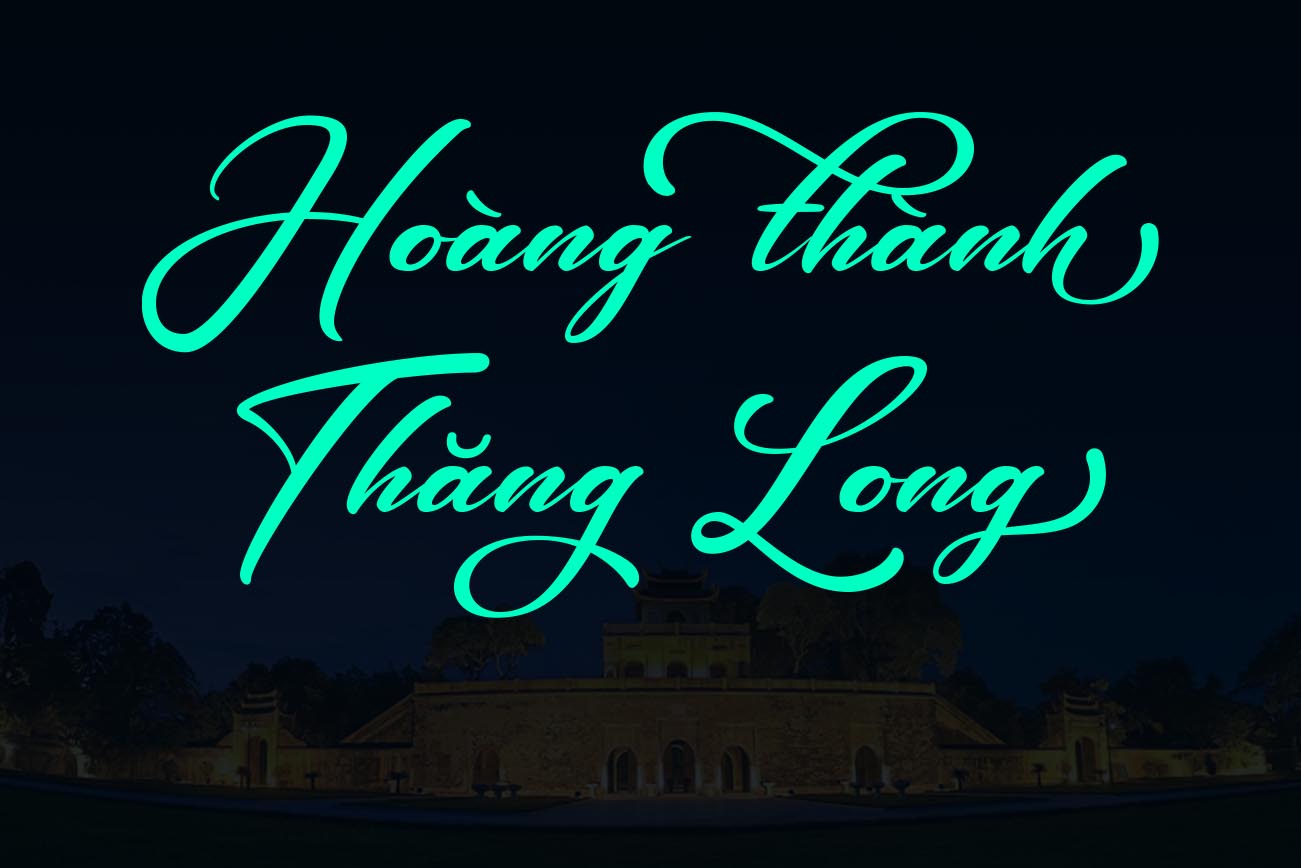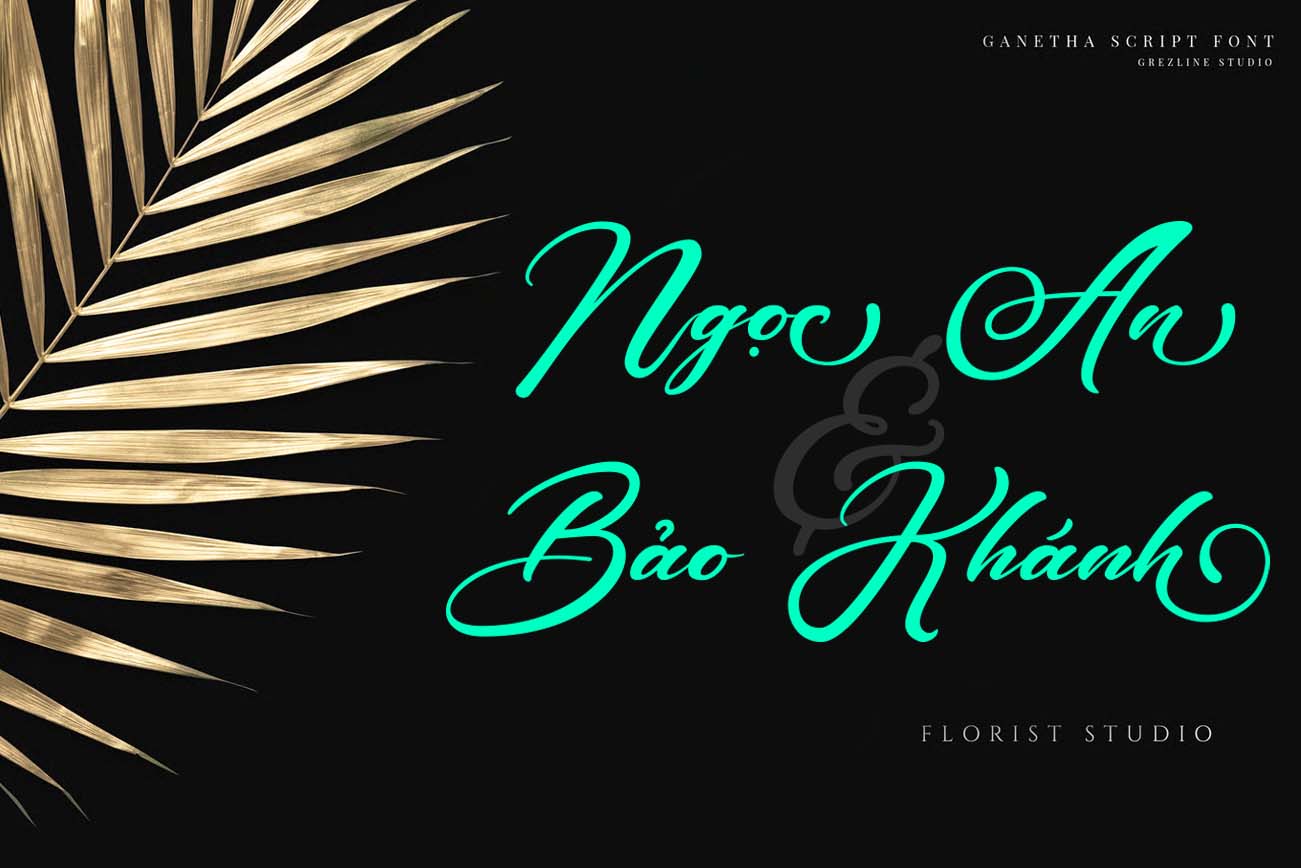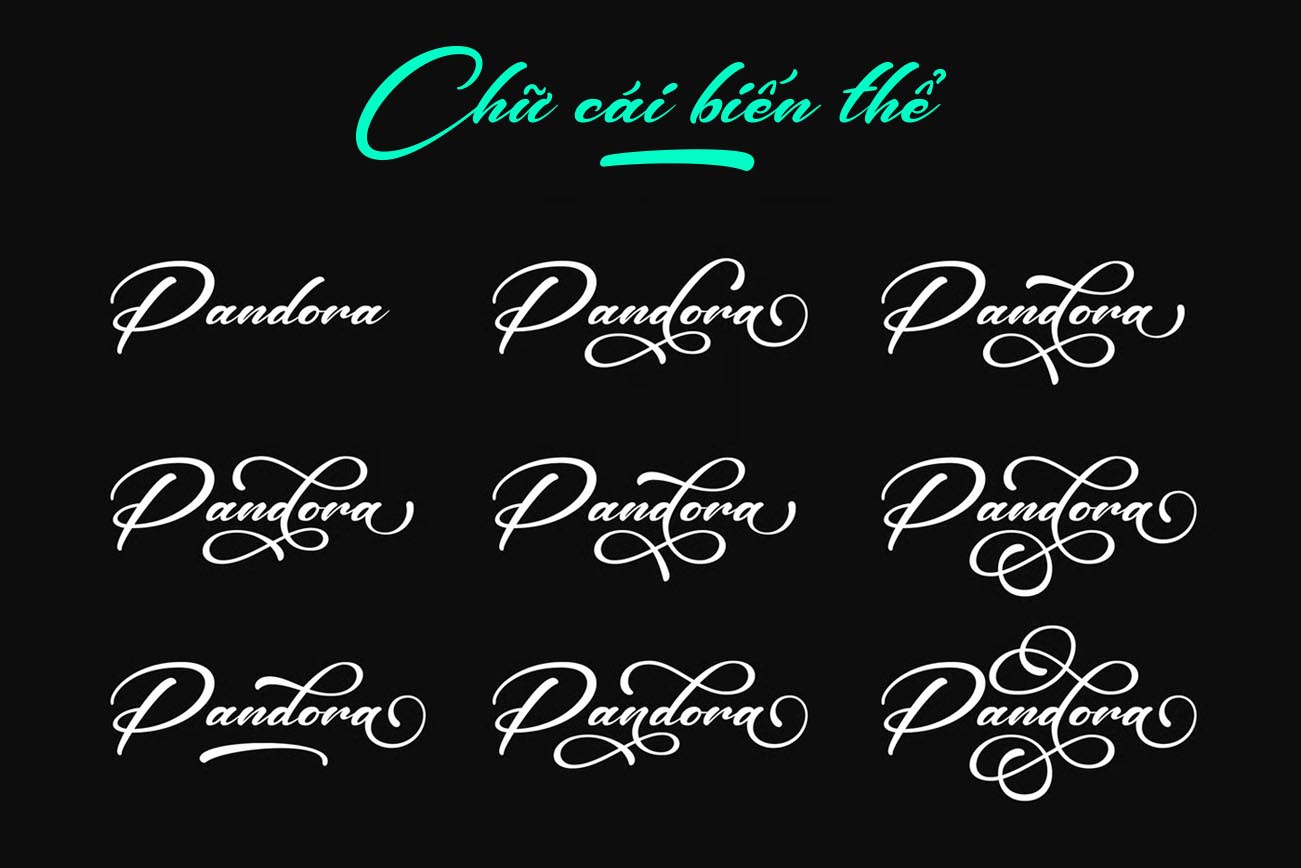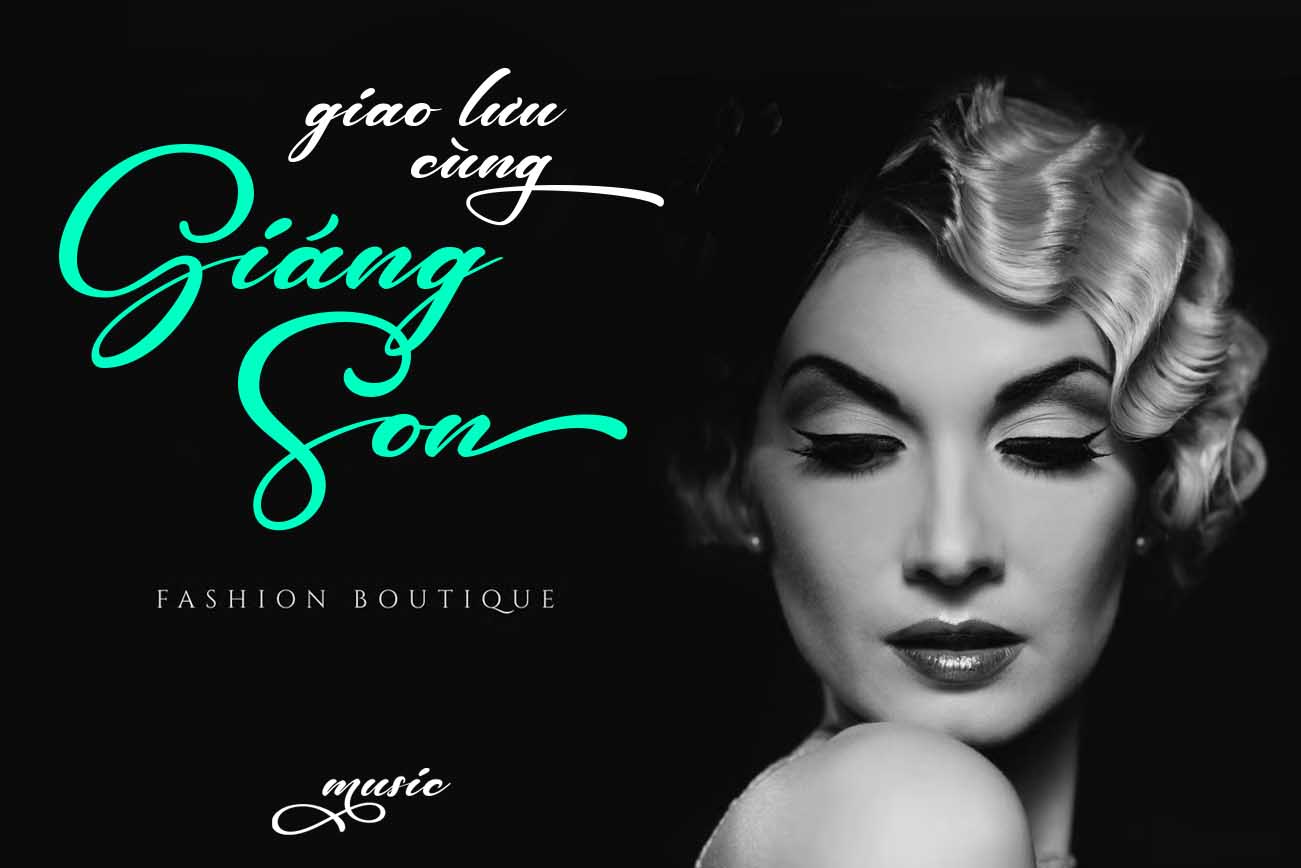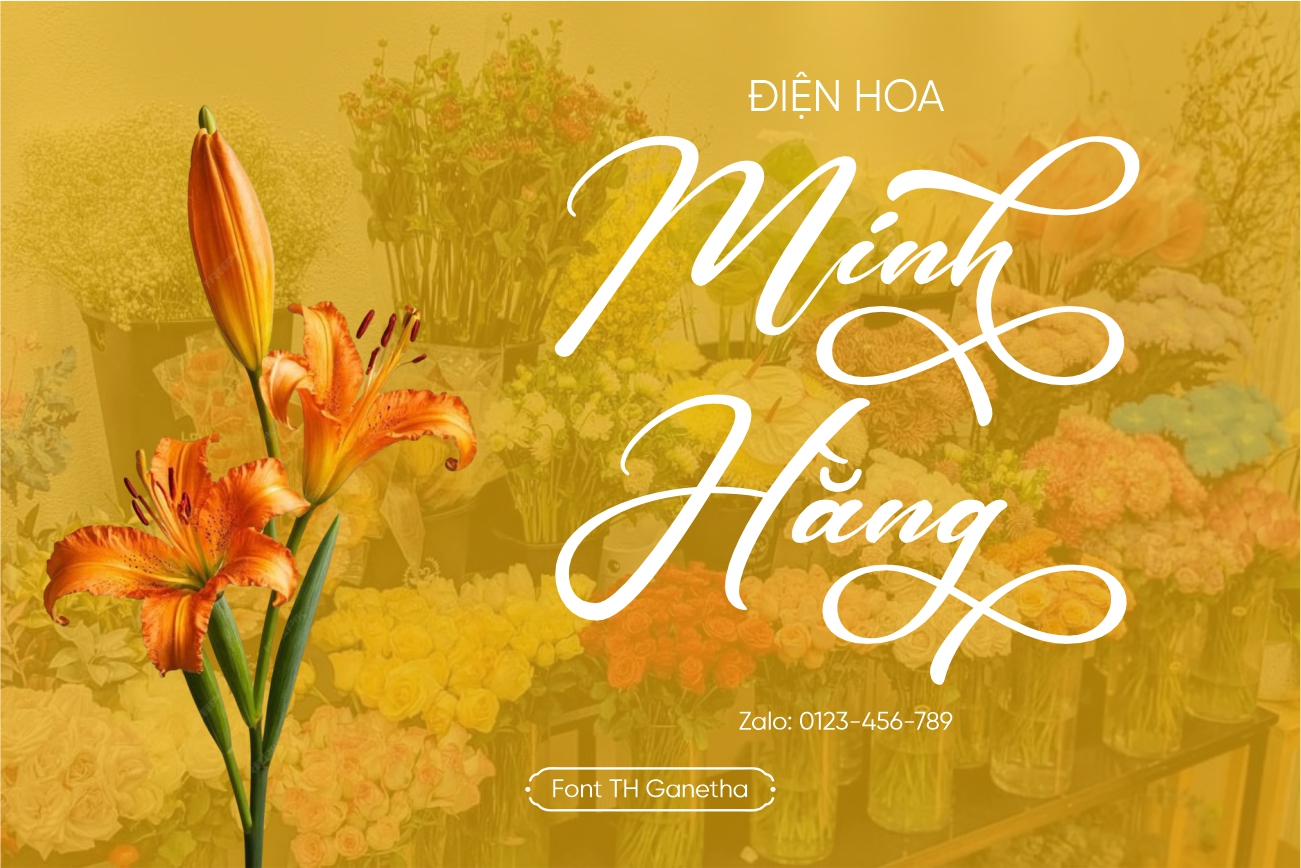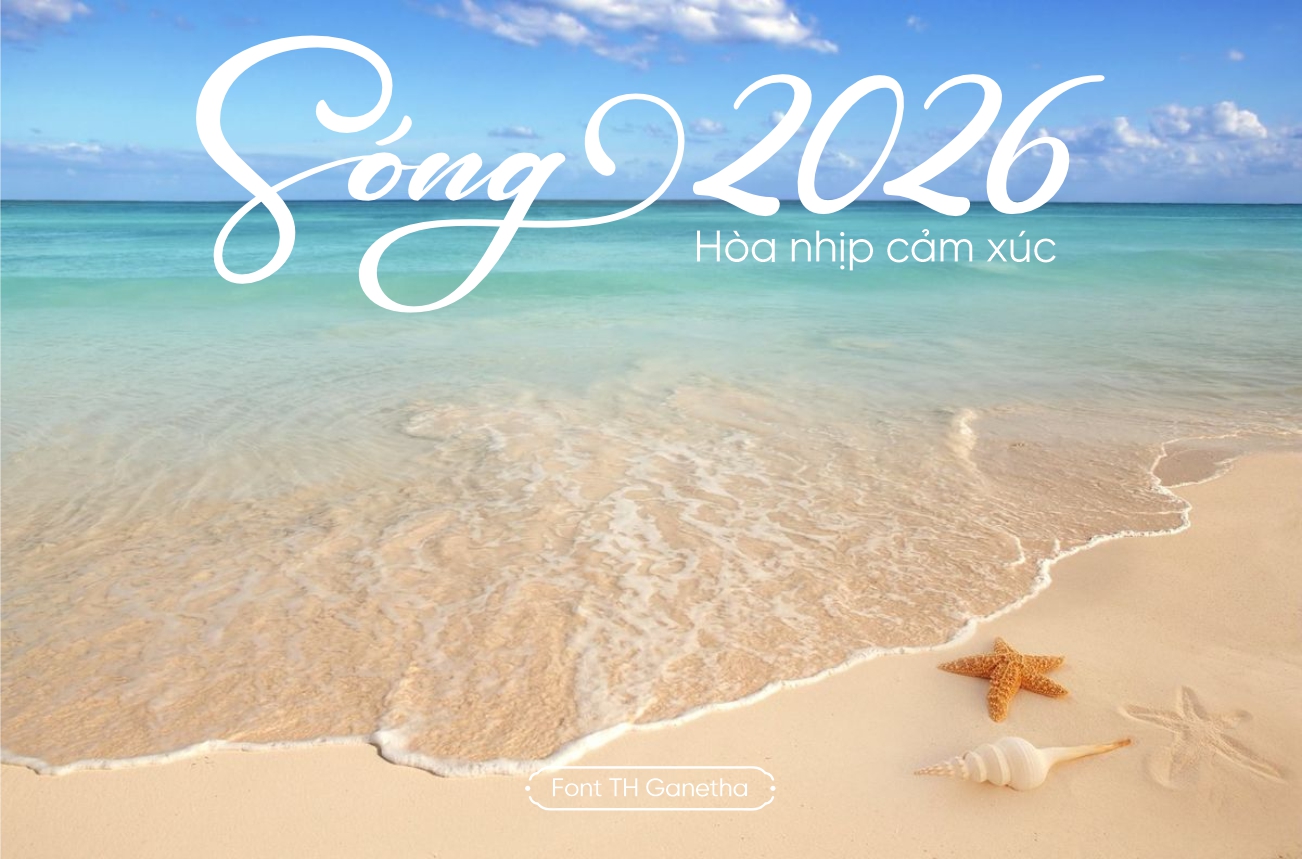
TH Ganetha – Font Thiệp Cưới Việt Hóa, Nét Chữ Mềm Mại Tinh Tế
Trong xu hướng thiết kế ngày cưới hiện đại, việc tìm kiếm một font việt hóa mềm mại có khả năng truyền tải trọn vẹn cảm xúc lãng mạn là ưu tiên hàng đầu của các Designer. TH Ganetha chính là câu trả lời hoàn hảo cho bài toán đó. Đây là phiên bản Việt hóa hoàn chỉnh của bộ font Ganetha đình đám, mang đậm phong cách thư pháp (Calligraphy) thủ công, giữ nguyên vẹn cái hồn tinh tế của từng đường nét nhưng đã được Team TH chăm chút kỹ lưỡng để tương thích hoàn toàn với dấu tiếng Việt.
Sức hút của TH Ganetha nằm ở hệ thống ký tự thay thế (Alternates) vô cùng phong phú. Với hơn 820 ký tự gốc (glyphs), font chữ này cho phép người dùng tùy biến các nét gạch chân, nét uốn lượn ở đầu và cuối chữ cái cực kỳ linh hoạt. Điều này biến TH Ganetha trở thành một font wedding lý tưởng, giúp tên của cô dâu và chú rể hiện lên như một tác phẩm nghệ thuật độc bản chứ không đơn thuần là văn bản đánh máy. Sự uyển chuyển trong từng nét nối tạo ra cảm giác sang trọng, cổ điển nhưng vẫn rất thời thượng, phù hợp với không gian tiệc cưới Luxury.
Không chỉ dừng lại ở vai trò là một font thiệp cưới xuất sắc, TH Ganetha còn là lựa chọn "đắt giá" cho các dự án xây dựng thương hiệu (Branding). Từ logo của các tiệm hoa, bao bì mỹ phẩm cao cấp cho đến các trích dẫn (Quote) tâm trạng trên mạng xã hội, font chữ này đều mang lại hiệu ứng thị giác mạnh mẽ về sự chau chuốt và đẳng cấp. Nếu bạn đang tìm kiếm một công cụ để "thổi hồn" vào các thiết kế cần sự bay bổng, TH Ganetha chắc chắn sẽ không làm bạn thất vọng.